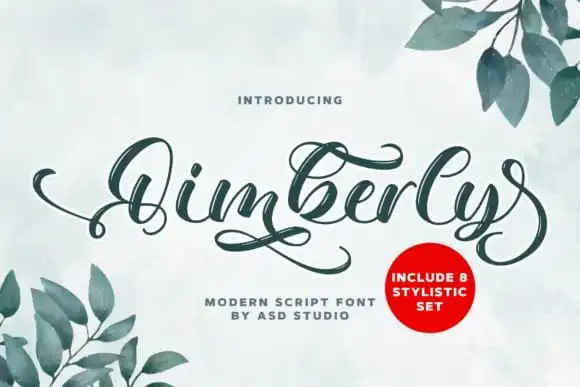
Qimberly Calligraphy Font – Download Grátis
Qimberly Calligraphy Font é uma fonte script que se destaca pela sua estética grossa, agressiva e forte, com um impressionante toque elegante, clássico e único. Este moderno tipo de escrita foi criado por Asd Studio, oferecendo sete conjuntos estilizados para tornar seu design mais atraente e belo. Esta fonte é perfeita para trazer qualquer projeto DIY à vida, transformando seus trabalhos em algo realmente especial. Qimberly Calligraphy Font tem o poder de criar designs irresistíveis que você pode usar para dar um toque único aos seus projetos pessoais ou profissionais.